La scelta del carattere giusto per il tuo logo è fondamentale. Non è solo una parte della tua immagine aziendale, ma anche un'espressione della tua personalità e del tuo lavoro. In questa guida scoprirai come scegliere il carattere giusto per il tuo logo da fotografo, quali caratteri si abbinano bene e quali caratteri comunichi con essi.
Principali osservazioni
- Scegli un carattere che si adatti al tuo stile personale e al tuo lavoro.
- Fai attenzione alla leggibilità del carattere, affinchè lo spettatore riconosca immediatamente il tuo nome.
- Non combinare più di due caratteri per mantenere chiarezza.
- I caratteri hanno personalità, che dovrebbero riflettere il tuo business.
Scelta del carattere in dettaglio
1. Le considerazioni fondamentali
Prima di tuffarti nel mondo apparentemente infinito dei caratteri, rifletti prima su chi sei e cosa caratterizza il tuo lavoro. Ogni dettaglio conta – dal fotografo di matrimoni al fotografo di prodotto, il tuo carattere dovrebbe riflettere ciò che fai.
2. La varietà dei caratteri
I caratteri possono essere suddivisi in diverse categorie. I gruppi noti sono:
- Caratteri sans-serif: Questi caratteri sono chiari, lineari e moderni. Sono facili da leggere e spesso sono la prima scelta per molti fotografi.
- Caratteri serif: Questi caratteri hanno piccole "zampe" alle lettere e migliorano la leggibilità, soprattutto nei testi a corpo. Sono adatti per branding di fotografi tradizionali ed eleganti.
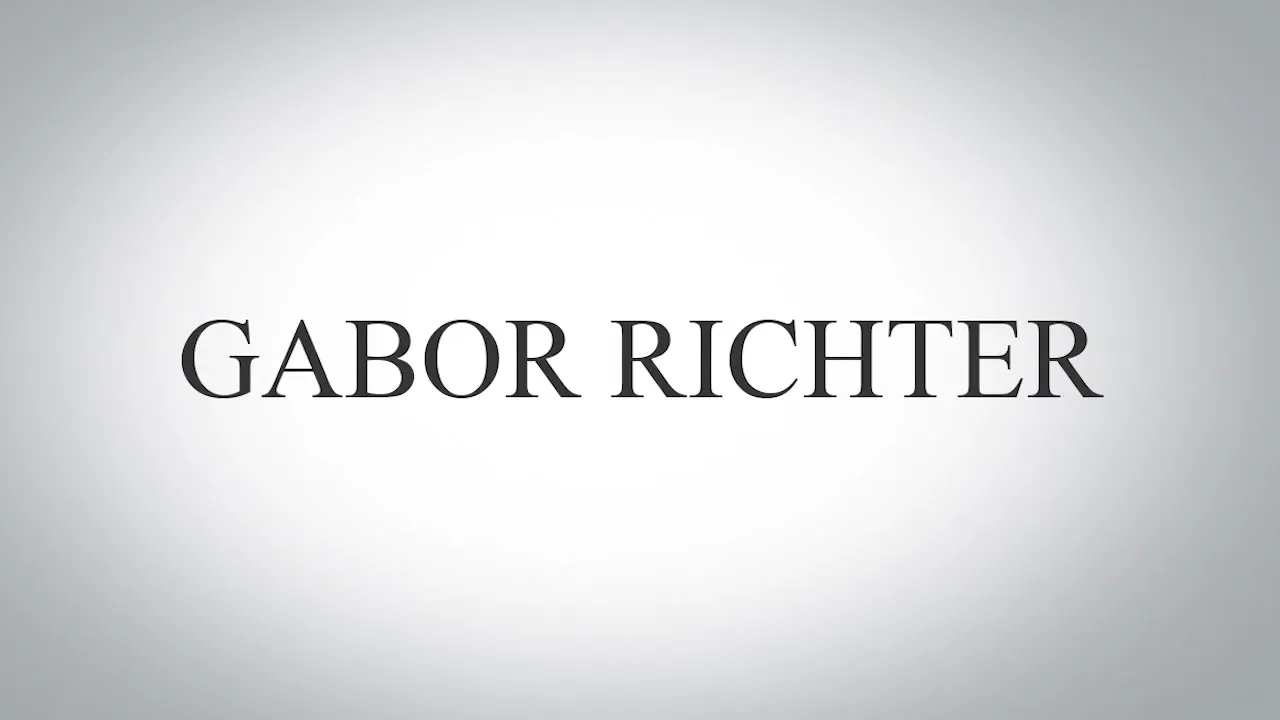
- Caratteri giocosi: Se incarnate uno stile creativo e non convenzionale, i caratteri giocosi potrebbero adattarsi a te. Fai però attenzione a non scegliere caratteri troppo eccentrici, affinchè restino leggibili nonostante il loro aspetto ludico.
- Caratteri decorati: Questi caratteri sono spesso difficili da leggere e sono adatti solo per applicazioni speciali. Se desideri utilizzare questo tipo di carattere, sceglilo con parsimonia e rifletti attentamente se contribuisce realmente al messaggio del tuo logo.
3. Il carattere giusto per il tuo stile fotografico
Ricorda che potresti porti la domanda: "Quale carattere si adatta a me?"
- Fotografi di matrimoni: Il loro lavoro ruota attorno alle emozioni, ai dettagli e alla passione. Qui potrebbe adattarsi bene una scrittura elegante e leggermente giocosa. È importante che resti ben leggibile anche se è stilosa.
- Fotografi di prodotto: Questi fotografi lavorano spesso in modo molto preciso e in un ambiente tranquillo. Un carattere chiaro e lineare potrebbe adattarsi perfettamente.
- Fotografi sportivi: Dinamica e movimento sono centrali per i fotografi sportivi. Caratteri professionali che trasmettono un senso di movimento sono un vantaggio.
- Fotografi gotici: Se il tuo focus è su temi molto specifici e duri, potrebbe adattarsi bene un carattere decorato o molto marcato. Assicurati che rimanga ancora leggibile.
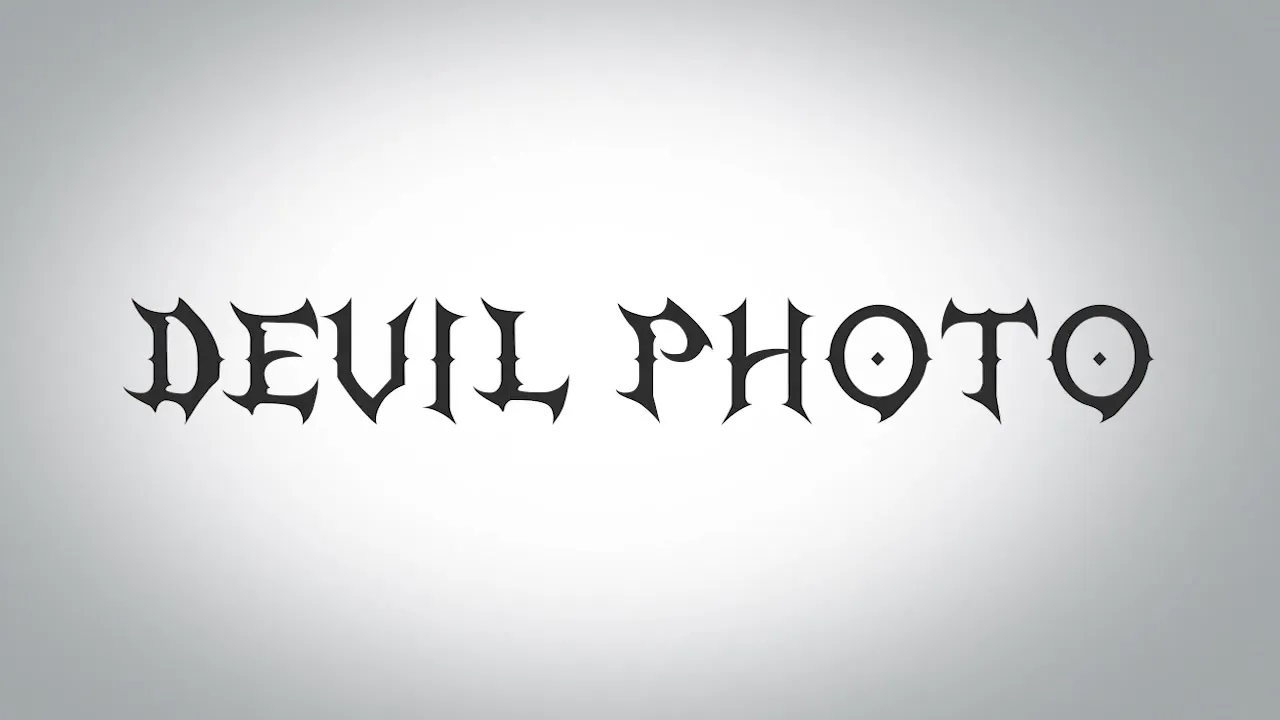
4. La combinazione di caratteri
Se desideri utilizzare più caratteri nel tuo logo, è importante che armonizzino tra loro. Utilizza al massimo due caratteri: uno per il titolo principale e uno discreto per i testi secondari o aggiuntivi.
Fai attenzione a scegliere caratteri che siano della stessa famiglia tipografica. Questo significa che possono esistere in varie varianti (come grassetto o corsivo), aumentando la flessibilità e facilitando la combinazione.
5. Il processo di scelta del carattere
Prenditi il tempo necessario per scegliere il carattere. La ricerca e la selezione del carattere giusto possono essere una sfida e spesso richiedono più tempo di quanto pensi. A volte possono volerci ore o addirittura giorni per trovare il carattere perfetto.
Fai annotazioni sul tuo stile e le tue preferenze. Queste informazioni ti aiuteranno a concentrarti su un numero ristretto di caratteri che corrispondono veramente a te e al tuo marchio.
Riepilogo – Scegliere il carattere giusto per il tuo logo da fotografo
La scelta del carattere è fondamentale per la prima impressione del tuo logo. Ricorda che non si tratta solo di estetica, ma anche di leggibilità e identità. Un carattere ben scelto può guadagnare la fiducia dei clienti e rafforzare il tuo marchio.
Domande frequenti
Quanto è importante la scelta del carattere per il mio logo?La scelta del carattere è fondamentale, poiché riflette il tuo stile e la tua professionalità.
Posso usare più di due caratteri in un logo?Si consiglia di utilizzare al massimo due caratteri per evitare confusione.
Come trovo il carattere adatto a me?Annota quali caratteristiche ed emozioni associ al tuo stile fotografico e cerca caratteri che le esprimano.
Tutti i caratteri giocosi sono adatti per il mio logo?I caratteri giocosi possono andare bene, ma fai sempre attenzione alla leggibilità e se si adattano al tuo stile.
Dovrei scegliere il mio carattere in varie varianti?Sì, le famiglie di caratteri ti offrono la possibilità di combinare elegantemente un carattere principale e testi secondari.